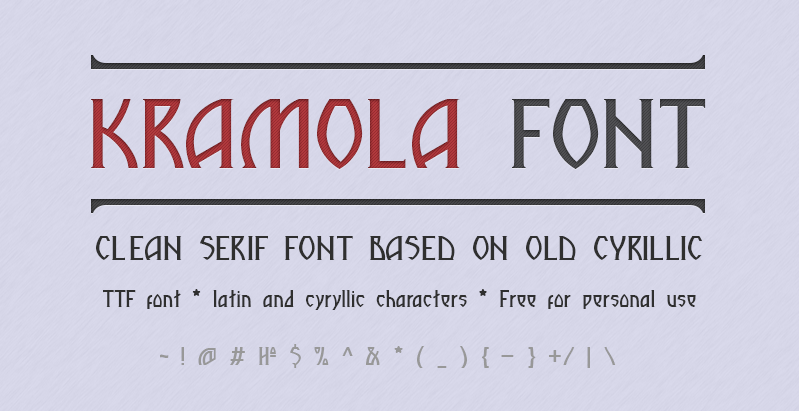
Kramola font – Download Grátis
Kramola é uma elegante fóntes serif que traz arquitetura na sua forma mais sofisticada. Desenvolvida pelo designer russo Aleksey Mednov, essa fonte personalizada oferece um estilo sóbrio e confiável ideal para projetos de escrita formal. Em termos de uso comercial, é importante notar que Kramola está disponível gratuitamente para fins pessoais, mas o usuário deve entrar em contato diretamente com o criador para qualquer necessidade de uso comercial. Para os amantes de recursos gráficos e desenhadores digitais, Kramola oferece uma opção única para adicionar um toque de elegância a qualquer projeto de texto, seja ele em design editorial, branding ou criação de logos.